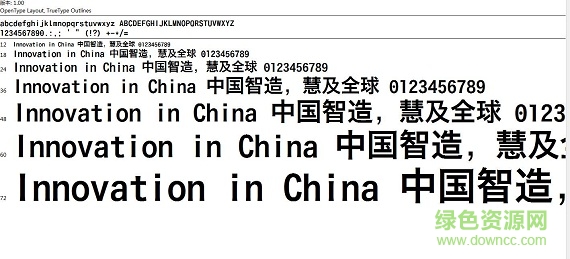
mingheimonob字體是一款明黑等寬粗體,所有的字符都是一樣寬度的,橫平豎直,干凈簡潔,屬于無襯線字體類,非常容易辨識和閱讀,歡迎大家免費(fèi)下載!
在漢字字體的一些黑體中也是有襯線的,一些字體在每個(gè)筆畫的端口都有一個(gè)喇叭口形狀的裝飾,這種裝飾源于早些時(shí)候的鉛字印刷的鉛字,由于當(dāng)時(shí)技術(shù)的限制,筆畫的端口會收縮,為了解決這個(gè)問題,當(dāng)時(shí)設(shè)計(jì)鉛字的工作人員就把黑體設(shè)計(jì)成喇叭口的。以致后來的計(jì)算機(jī)時(shí)代,在設(shè)計(jì)首批黑體的時(shí)候,參照了有喇叭口裝飾的黑體!